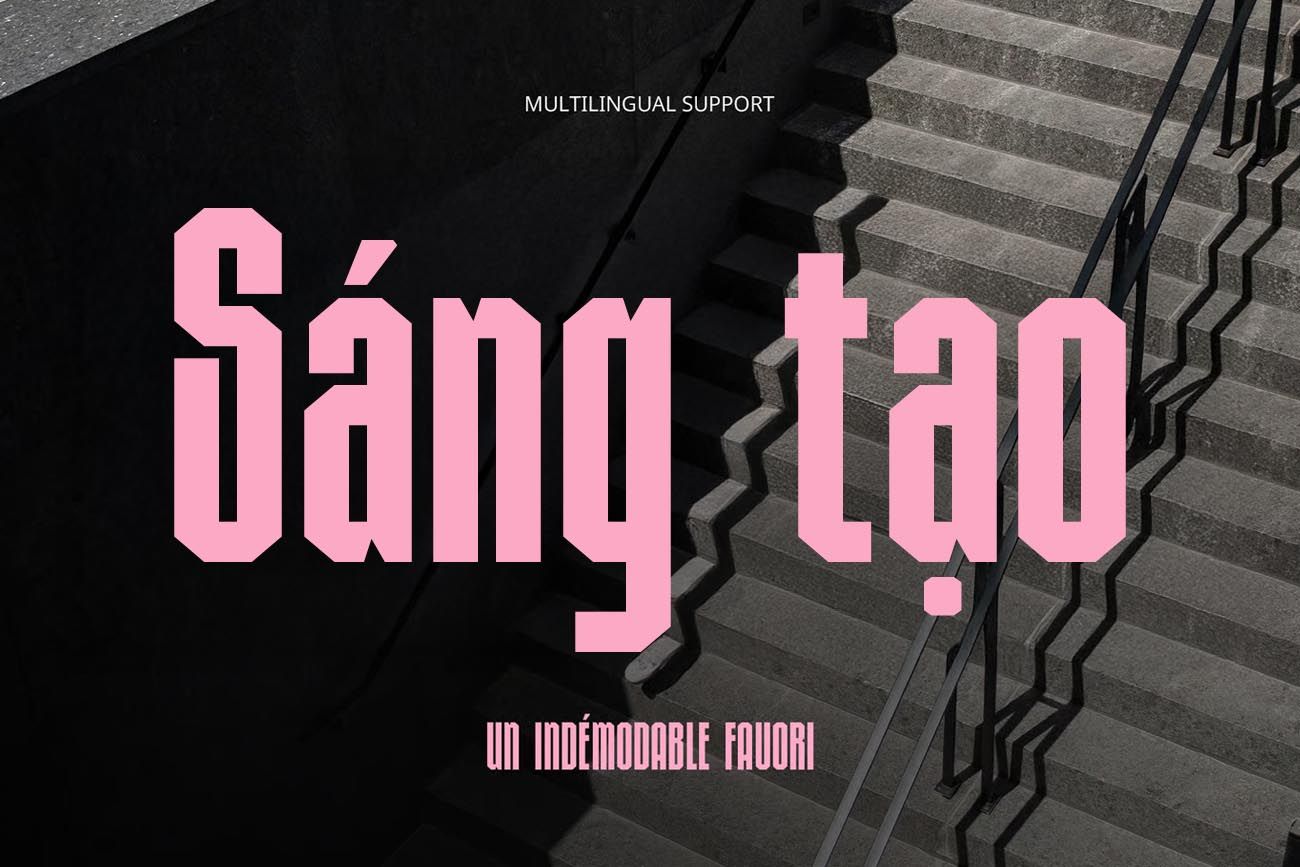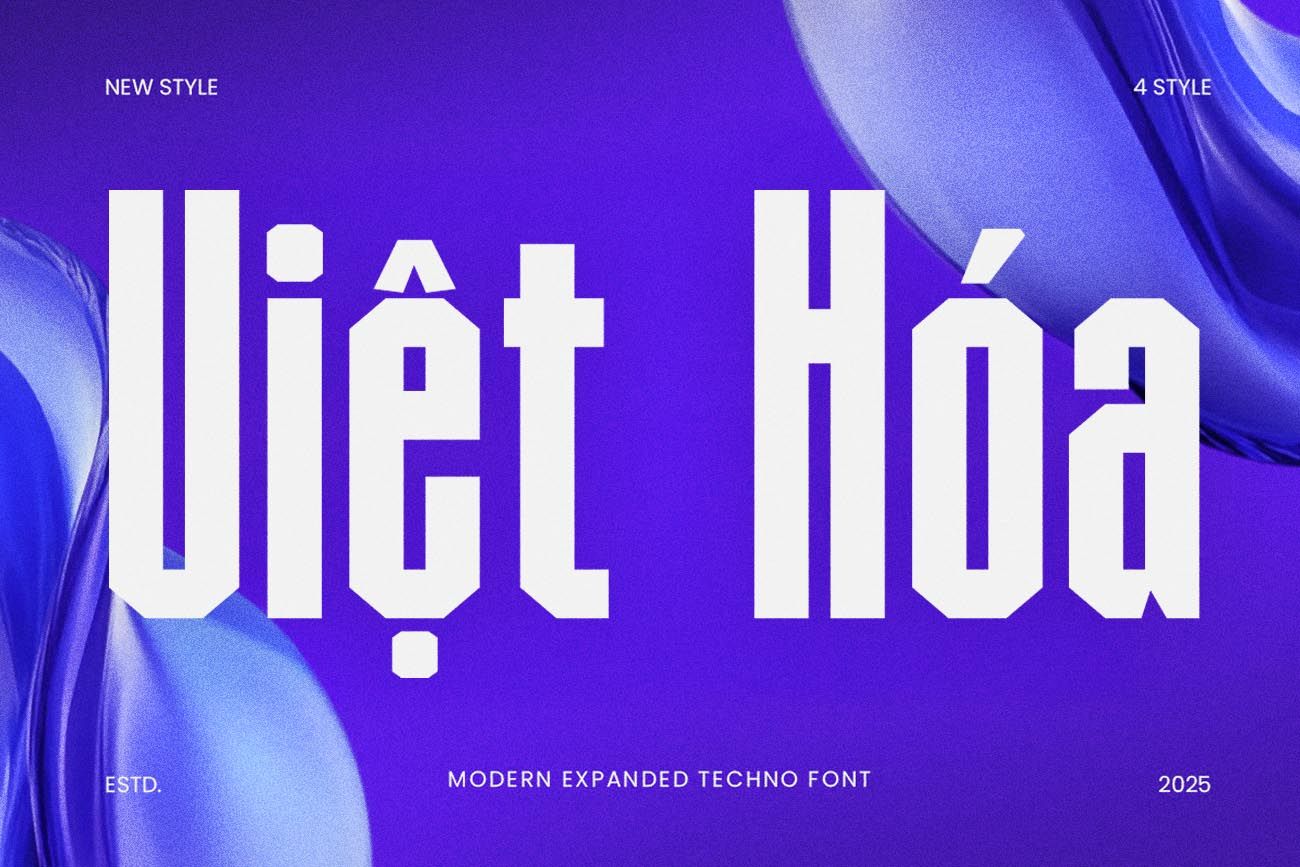
Bạn đang tìm kiếm một font chữ mạnh mẽ, mang phong cách hiện đại, cá tính và đậm chất thể thao? Astrophel chính là lựa chọn hoàn hảo. Với thiết kế condensed sans-serif sắc sảo, font chữ này không chỉ nổi bật ở nét thẩm mỹ góc cạnh mà còn thể hiện sự chuyên nghiệp, bản lĩnh và tốc độ trong từng dòng chữ. Phiên bản Việt hóa của TH Astrophel Font hiện đã có mặt, hỗ trợ đầy đủ dấu tiếng Việt và giữ trọn vẹn tinh thần thiết kế gốc.
TH Astrophel là font chữ condensed, tức các chữ cái được thiết kế hẹp lại theo chiều ngang nhưng cao và rõ ràng. Điều này giúp tiết kiệm không gian hiển thị, đồng thời tạo cảm giác sắc bén, mạnh mẽ và tập trung. Mỗi ký tự được cắt gọt với đường thẳng cứng cáp, góc vuông hoặc vát nhẹ – mang đến vẻ đẹp hình học cứng cáp, rất phù hợp cho các dự án cần thể hiện sự dứt khoát, vận động, và tinh thần thể thao tốc độ.
Font được Việt hóa chỉn chu bởi Phạm Sơn – Admin S99.vn, với đầy đủ bộ dấu, ký tự đặc biệt và hỗ trợ Unicode. Các glyph dấu thanh như sắc, huyền, hỏi, ngã được căn chỉnh cân đối, đảm bảo hiển thị tốt trên mọi nền tảng thiết kế, từ in ấn đến giao diện số.
Tiêu đề poster phim hành động, thể thao, viễn tưởng
Logo thương hiệu thể thao, startup fitness, xe đua
Bìa tạp chí nam tính, mô tô – ô tô
Banner giải đấu thể thao, tiêu đề social media
Bao bì sản phẩm đồ tập, thiết bị vận động
Font TH Astrophel đặc biệt phù hợp với các thiết kế mạnh mẽ, thể thao và cá tính – nơi mà thông điệp cần được truyền tải ngay lập tức và ấn tượng sâu sắc.